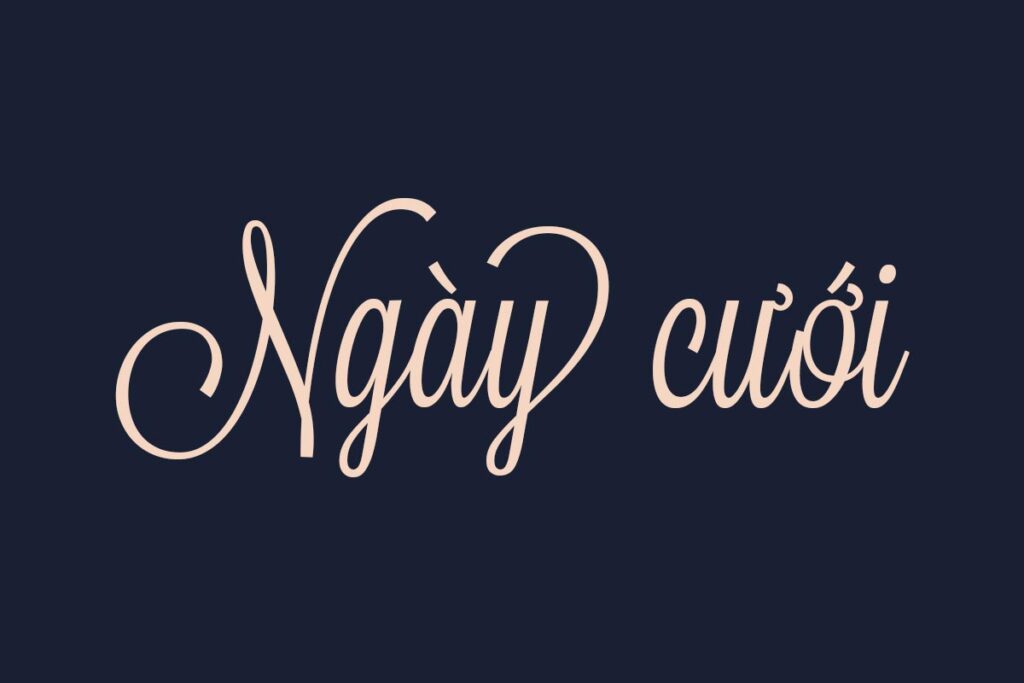
Hệ thống font UVF là một trong những bộ sưu tập phông chữ Việt hóa đồ sộ, tập hợp đa dạng phong cách từ hiện đại, tối giản đến cổ điển và nghệ thuật viết tay. Việc sở hữu trọn bộ tài nguyên này giúp các kiến trúc sư, kỹ sư và nhà thiết kế dễ dàng tìm kiếm giải pháp kiểu chữ phù hợp cho từng bản vẽ phối cảnh, hồ sơ kỹ thuật hay bộ nhận diện thương hiệu công trình.
Khám phá những ưu thế nổi bật của hệ thống font UVF trong thiết kế
Điểm giá trị của dòng phông này nằm ở tính bao quát và sự đồng bộ về mặt kỹ thuật. Bộ font UVF tập hợp các kiểu chữ quốc tế nổi tiếng nhưng đã được tinh chỉnh toàn diện về bảng mã Unicode tiếng Việt. Các dấu thanh được đặt ở vị trí cân đối, tỷ lệ hài hòa với thân chữ, giúp văn bản duy trì được cấu trúc thẩm mỹ nguyên bản. Điều này mang lại sự mạch lạc, giúp hồ sơ dự án của bạn thể hiện được tính chuyên nghiệp từ các dòng ghi chú kỹ thuật nhỏ đến các tiêu đề lớn.
Sự đa dạng của kho phông chữ này còn mang đến sự linh hoạt tối đa cho người làm nghề. Thay vì phải tìm kiếm từng phông chữ rời rạc, việc tải trọn bộ font UVF tiếng Việt cung cấp giải pháp toàn diện cho mọi phong cách kiến trúc, từ công nghiệp, hiện đại đến hoài cổ. Khả năng hiển thị sắc nét trên cả màn hình kỹ thuật số và các bản in khổ lớn giúp các ấn phẩm truyền thông hay bảng hiệu công trình luôn duy trì được chiều sâu thị giác ổn định.
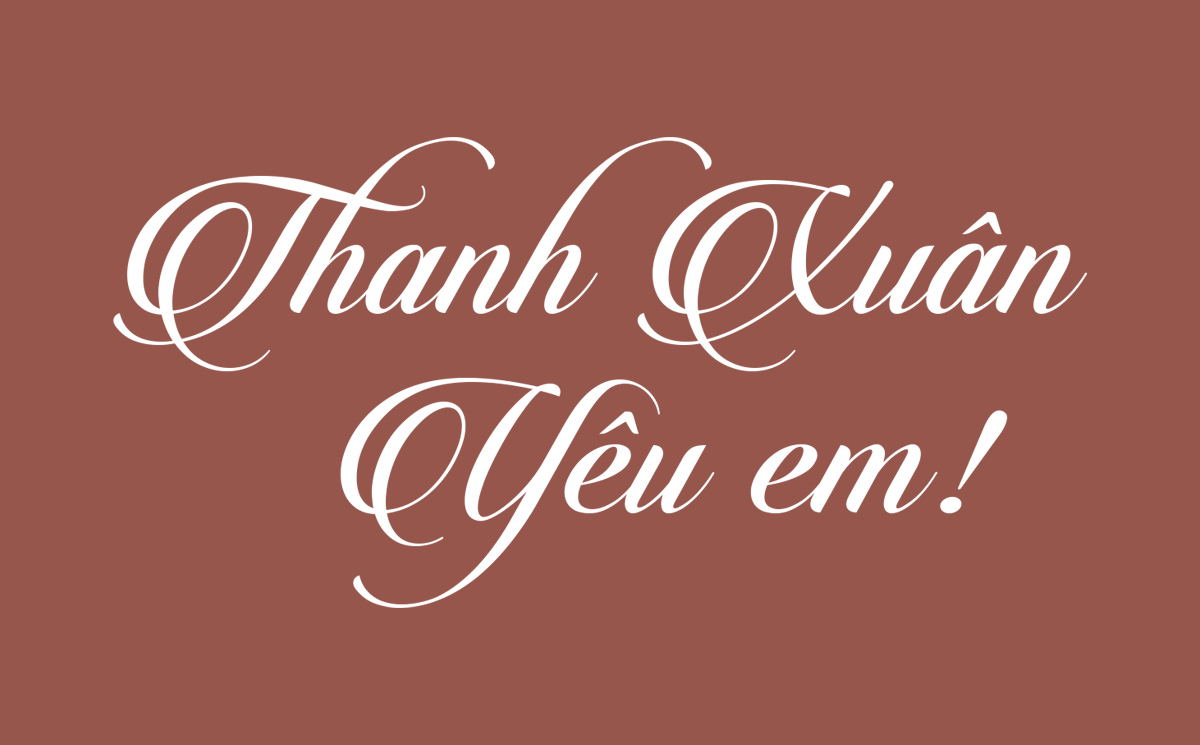
Tư vấn từ chuyên viên: Khi thực hiện download font UVF, bạn nên phân loại phông chữ theo từng mục đích cụ thể: dùng các kiểu không chân cho phần mô tả kỹ thuật và sử dụng các kiểu chữ có chân hoặc nghệ thuật cho phần tiêu đề dự án. Sự phân cấp rõ ràng này sẽ giúp bản thiết kế của bạn có cấu trúc chặt chẽ và dễ tiếp nhận thông tin hơn.
03 Ứng dụng phông chữ UVF vào thực tế công trình kiến trúc
Nhờ sự phong phú về kiểu dáng và tính ứng dụng cao, việc sử dụng các mẫu chữ từ bộ download font UVF Việt hóa mang lại giá trị thực tế lớn trong khâu thiết kế và thi công:
- Hệ thống nhận diện cho Homestay & Khu nghỉ dưỡng: Sử dụng các dòng phông nghệ thuật trong bộ UVF cho biển tên phòng, bảng chỉ dẫn nội khu bằng gỗ hoặc mica gương giúp không gian toát lên vẻ thư thái, thu hút du khách yêu thích trải nghiệm không gian sống xanh.
- Ghi chú thông số trên bản vẽ kỹ thuật: Độ rõ nét của các kiểu chữ không chân trong bộ UVF hỗ trợ đắc lực cho kỹ sư khi trình bày thông số vật liệu panel, kết cấu dầm thép, giúp đội ngũ thi công tại hiện trường tra cứu thông tin nhanh chóng.
- Thiết kế hồ sơ năng lực và Profile dự án: Sử dụng font UVF giúp các trang thuyết minh phương án kiến trúc trở nên mạch lạc, thể hiện tư duy thẩm mỹ hiện đại và phong cách làm việc bài bản của đơn vị thi công đối với chủ đầu tư.
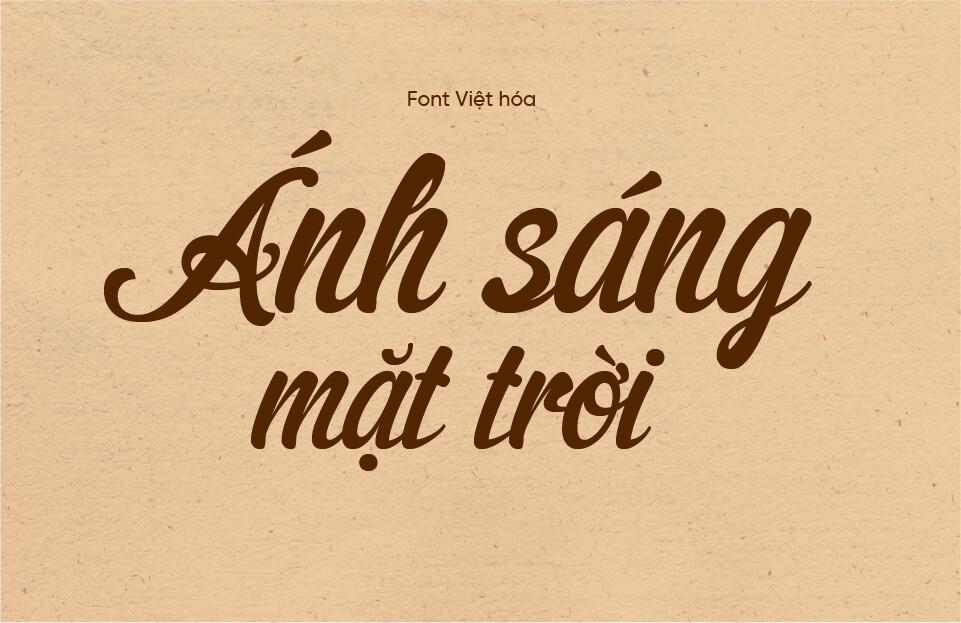
03 Lưu ý khi trình bày bố cục bản vẽ với font UVF đạt hiệu quả cao
Để khai thác hiệu quả vẻ đẹp của dòng phông đa năng này mà không làm rối mắt người xem, người thiết kế nên lưu tâm một số kinh nghiệm sau:
- Hạn chế sử dụng quá nhiều kiểu chữ: Trong cùng một bản vẽ hoặc hồ sơ báo giá, bạn chỉ nên phối hợp từ 2 đến 3 kiểu phông UVF khác nhau để duy trì tính đồng bộ và sự trang trọng cho tài liệu.
- Kiểm soát khoảng cách dòng: Với các dòng phông có chân hoặc phông nghệ thuật, bạn nên thiết lập khoảng cách dòng thoáng một chút để các dấu thanh tiếng Việt không bị chồng lấn, giữ được độ sắc sảo cho văn bản khi in ấn trên khổ giấy lớn.
- Lựa chọn độ đậm phù hợp với vật liệu: Khi thiết kế cắt chữ nổi CNC hoặc laser cho các biển hiệu nhà lắp ghép, hãy ưu tiên các biến thể Bold có nét chữ dày dặn để cấu trúc chữ đủ chắc chắn sau khi gia công thực tế.